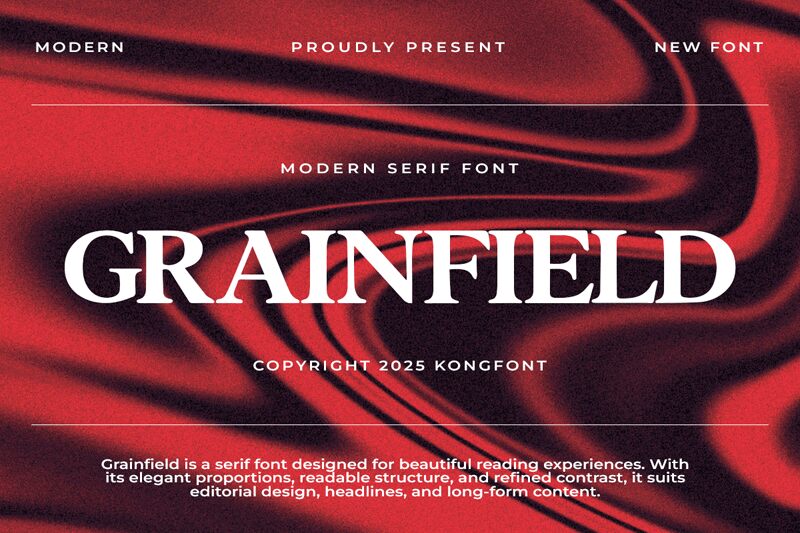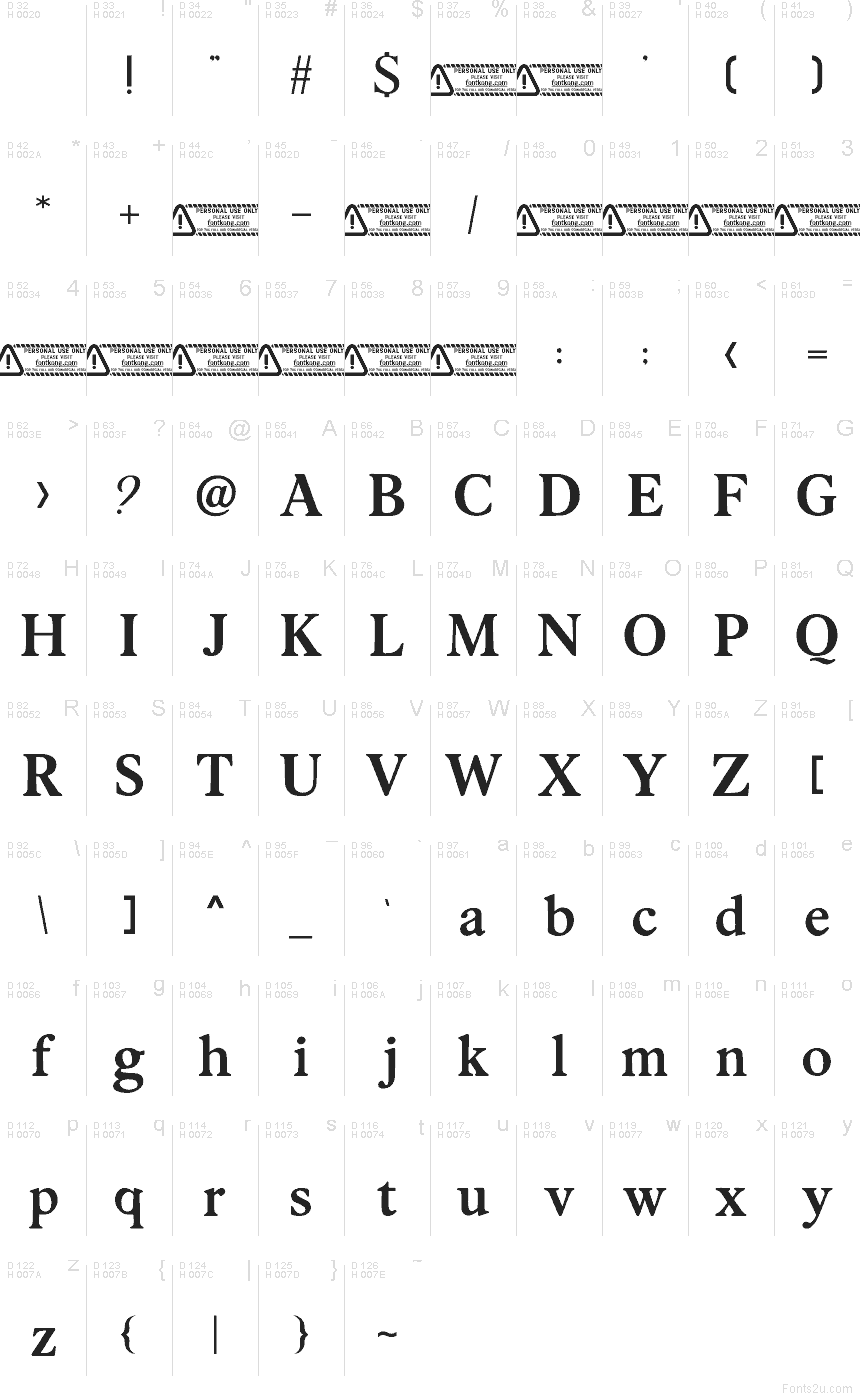
Grainfield, eine kostenlose Serifenschrift im Old-Style-Look von Typeface - Kong Font, versprüht den warmen Charme eines Märchenbuchs. Geprägt durch tropfenförmige Serifen und weich geschwungene Linien wirken die Buchstaben weniger starr als vielmehr fast kalligrafisch. Mit ihren abgerundeten Verbindungen und einem leicht rustikalen Rhythmus wirkt die Schrift nahbar und nicht zu förmlich.
Damit eignet sie sich perfekt für Buchcover, Café-Branding, Verpackungen, redaktionelle Zitate oder Einladungsüberschriften – überall dort, wo eine kostenlose Schrift mit handgemachtem Serif-Charakter lebendiger wirken soll als ein poliertes Design. Auch für kurze Logos, Titelkarten und Monogramme ist sie ideal, denn die geschwungenen Details und die dunkle, tintenartige Anmutung verleihen selbst kurzen Wörtern eine geerdete, literarische Stimmung.